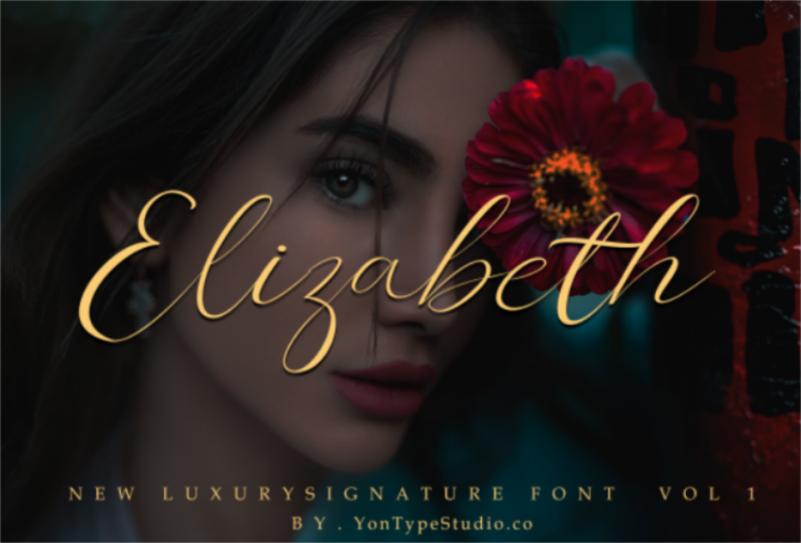
Elizabeth Luxury Signature Font – Download Grátis
A Elizabeth Luxury Signature Font é a escolha perfeita para os criadores de designs que procuram uma fonte elegante e sofisticada para seus trabalhos de design editorial, logotipos ou materiais de marca personalizados. Este recurso gráfico hand-writtend (Handwritten Fonts) vem da designer talentosa yontype, conhecida por suas criações únicas e extremamente detalhadas. O que torna esta fonte tão especial é a sua característica escrita ao vivo, criando um toque autêntico e único em qualquer projeto. Os traços suaves e finos da Elizabeth Luxury Signature Font se sobressaem, oferecendo uma sensação de elegância e sofisticação que é perfeita para criar designs profissionais e atraentes. Se você está interessado em explorar ainda mais o potencial desta fonte ou se deseja adquirir um license comercial, yontype também disponibiliza uma versão completa com várias opções de licenciamento. Se você gostou deste recurso gráfico hand-writtend, certamente vai apreciar sua versão completa. Além disso, a designer também solicita doações para financiar seu trabalho e projetos futuros. Elizabeth Luxury Signature Font é mais que uma fonte; ela é um investimento no seu estilo de design. Seja você um profissional ou apenas iniciante na área, esta fonte será uma ferramenta valiosa em sua coleção. Não hesite em experimentar a Elizabeth Luxury Signature Font e deixe-nos saber como ela pode ajudá-lo a expressar ainda mais seu talento no design.